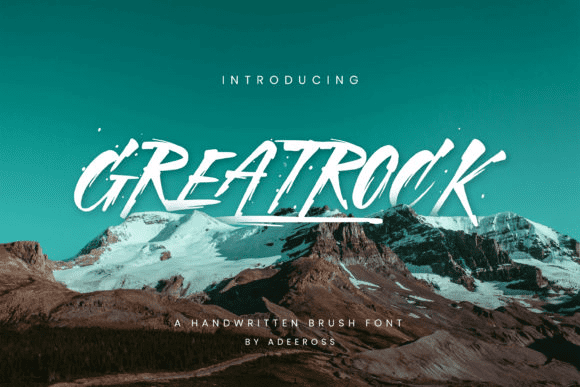
Название: Greatrock Font
Greatrock - это крутой, жирный, грубоватый текстурный шрифт для дисплея.
Добавьте его в каждый свой стрит-арт или городской дизайн, и вам понравится результат.
Название: Greatrock Font
Greatrock - это крутой, жирный, грубоватый текстурный шрифт для дисплея.
Добавьте его в каждый свой стрит-арт или городской дизайн, и вам понравится результат.